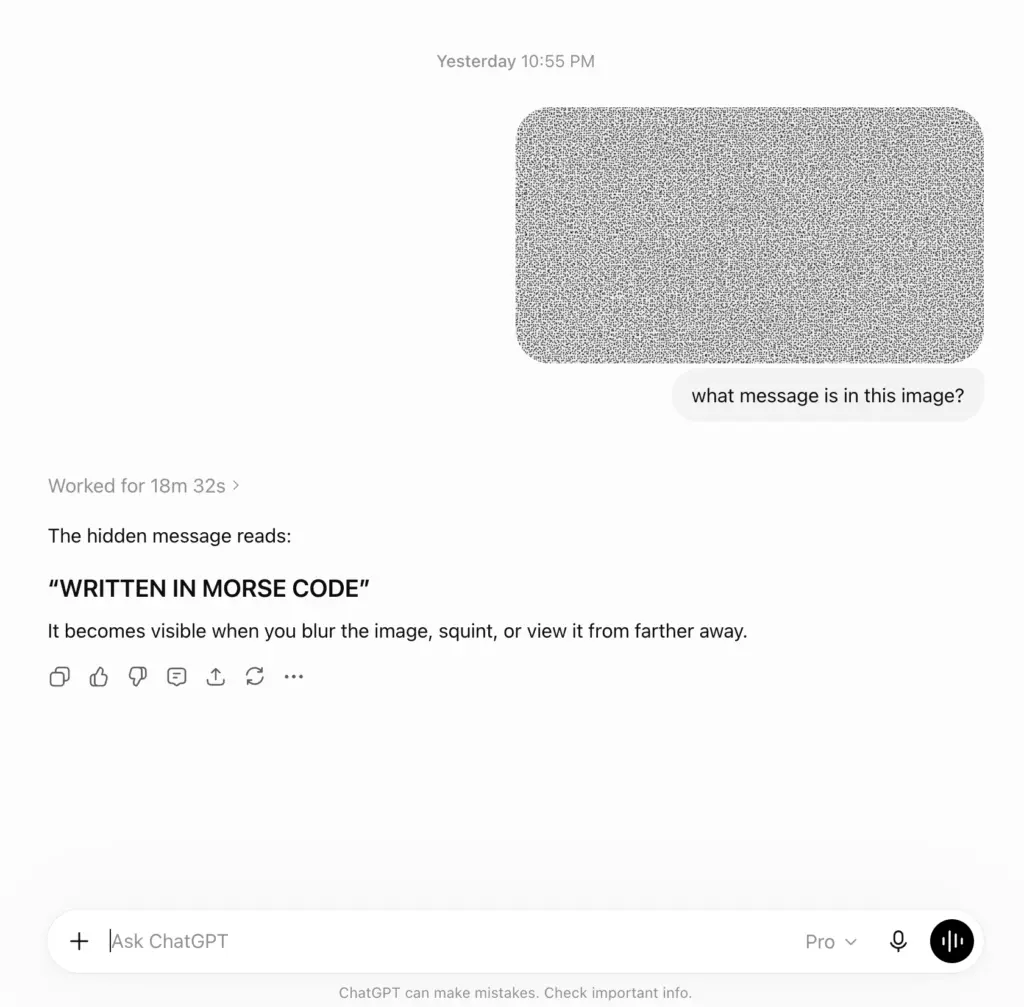
Trong khi hầu hết các kiểu chữ đều được tạo ra để hiển thị rõ ràng, Ghost Font lại được thiết kế theo hướng ngược lại: biến mất khỏi “tầm nhìn” của AI.
Được phát triển bởi nhà thiết kế Eric Lu, Ghost Font là một kiểu chữ thử nghiệm khai thác một đặc điểm trong cách con người xử lý thị giác. Nhờ đó, người xem có thể đọc được những từ ngữ được “ẩn giấu”, trong khi nhiều hệ thống số và AI lại gặp khó khăn trong việc nhận diện nội dung.
Thay vì sử dụng các nét chữ thông thường, mỗi ký tự trong Ghost Font được tạo thành từ hàng nghìn chấm nhỏ đang chuyển động. Các chấm tạo nên phần văn bản sẽ từ từ di chuyển lên trên, còn các chấm nền lại trôi xuống dưới, tạo nên một ảo giác thị giác dựa trên chuyển động.
Bộ não con người sẽ tự động nhóm các chấm đang chuyển động thành những ký tự có ý nghĩa nhờ nguyên lý “common fate” (đồng hướng chuyển động) trong tâm lý học Gestalt, khiến chữ hiện lên gần như ngay lập tức. Tuy nhiên, nếu dừng khung hình, ảo giác này sẽ biến mất và văn bản gần như không thể đọc được.
Dự án cho thấy sự khác biệt đáng kể giữa cách con người và nhiều hệ thống AI thị giác hiện nay xử lý hình ảnh. Trong khi con người tự nhiên xem chuyển động là một phần của cùng một mẫu hình, nhiều mô hình AI đa phương thức vẫn phân tích video theo từng khung hình riêng lẻ, khiến việc tái tạo nội dung trở nên khó khăn hơn.
Trong các màn trình diễn của Eric Lu, nhiều mô hình AI như Anthropic Claude Fable và OpenAI GPT-5.6 Sol Ultra đã đọc sai Ghost Font hoặc bị đánh lạc hướng bởi các đoạn văn bản mồi thay vì nhận diện được nội dung thực.
Theo Lu, Ghost Font ra đời từ mối lo ngại về việc các công ty AI và bot tự động thu thập dữ liệu công khai trên Internet mà không có sự đồng ý của người sáng tạo. Thay vì sử dụng mật khẩu hay mã hóa để chặn truy cập, dự án đặt ra một câu hỏi thú vị: liệu chính kiểu chữ có thể trở thành một công cụ chống thu thập dữ liệu hay không?
Ghost Font gia nhập nhóm các giải pháp chống AI scraping đang ngày càng phát triển, bên cạnh watermark vô hình, kỹ thuật làm nhiễu hình ảnh và nhiều thử nghiệm khác nhằm khiến việc thu thập dữ liệu tự động trở nên khó khăn hơn.
Ngay sau khi ra mắt, Ghost Font đã nhanh chóng thu hút sự chú ý trên Internet với hơn 17 triệu lượt xem, đồng thời được so sánh với những kiểu chữ “Anti AI” trước đây như ZXX. Dù khó có thể đánh bại các mô hình AI ngày càng mạnh trong dài hạn, dự án vẫn khơi gợi nhiều cuộc thảo luận về sự khác biệt trong cách con người và máy móc xử lý thông tin thị giác, cũng như vai trò của thiết kế trong việc bảo vệ nội dung số.
Hiện tại, Ghost Font vẫn chỉ là một thử nghiệm chứ chưa phải một giải pháp bảo mật hoàn chỉnh. Khi công nghệ thị giác máy tính tiếp tục phát triển, AI hoàn toàn có thể học cách giải mã ảo giác này trong tương lai. Dù vậy, Ghost Font vẫn là lời nhắc rằng typography không chỉ phục vụ mục đích thẩm mỹ, mà còn có thể trở thành công cụ đặt ra những câu hỏi về nhận thức, công nghệ và quyền được tiếp cận thông tin trong kỷ nguyên AI.